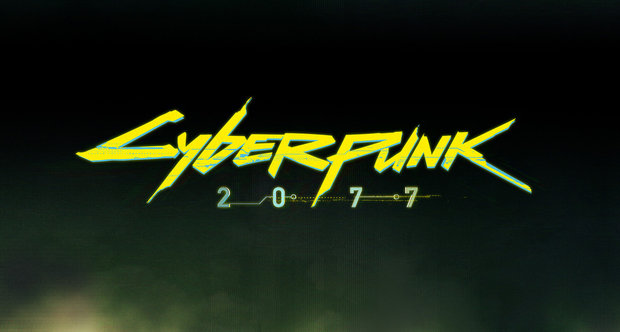
Что за шрифт используется в лого CyberPunk 2077
Отчень надо шаблон этого шрифта, можешь скинуть?)
В дополнение к находкам и прочему, прикрепляю еще один, схожий, шрифт.
быть может кому понравится)
Название шрифта - Street Gathering
подсказали(чел занимается шрифтами вплотную), что это реально самоделка
Работаю графическим дизайнером, сам недавно искал этот шрифт. Так вот, сидя на работе, в шутку побаловавшись с этой надписью, я пришел к выводу, что данный шрифт, CD Project RED все таки сделали сами, так что может быть в будущем после выхода оной игры, в сеть попадет и этот их собственный шрифт. Специально, выкладываю скрин своего баловства в фотошопе. Не скажу что прям наверняка, но допускаю такую возможность, что некоторые из этих шрифтов, были использованы для создания данного лого. В знак доброй воли, приведу названия заюзаных мной шрифтов =D
Death Knell
Abrahams Wish
Story Brush Slanted
Outrum Future
Ну и собственно, баловство =D
Я нашель)
Нашел более менее подходящий шрифт. Ссылка:
Наслаждайтесь! похоже что етот похож на 90% хотя.. смотрите сами
И там и там?
Могу скинуть оригинальный шрифт сyberpunk 2077
Скриншот необходимого шрифта
Ищу данный шрифт уже второй год, никак не могу найти; находил различные модификации, но не такие какие нужны.
Каждый из них отличается от нужного результата
Порой мне кажется, что его попросту не существует, однако сомнения вызвает то, что он используется не только в Cyberpunk 2077:
Логотип Java игры "Сyberpunk The Arasaka’s Plot"
есть и другие примеры, но искать просто их не охота.
Так что если кто-либо знает, что же за шрифт используется, прошу помочь =)